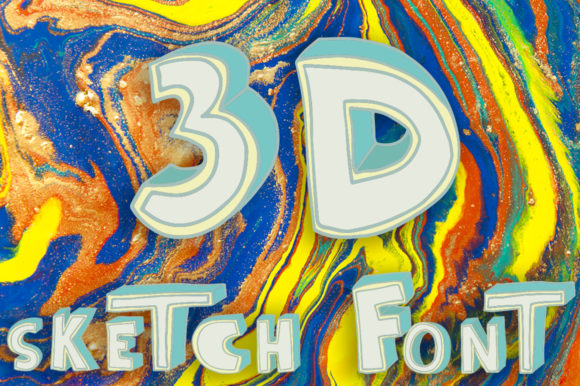
3D Sketch
Ulasan Mendalam: 3D Sketch – Font Display Urban yang Trendi
Jika Anda sedang mencari font display yang mampu menambah kesan modern dan urban pada desain grafis, 3D Sketch adalah pilihan yang tepat. Font ini memadukan gaya tiga dimensi dengan sentuhan street‑art, menjadikannya sangat versatile untuk berbagai proyek kreatif.
Keunggulan Utama 3D Sketch
- Desain 3D yang mencolok – Memberikan efek kedalaman yang membuat teks “melompat” dari latar belakang.
- Gaya urban & trendi – Cocok untuk branding streetwear, poster musik, event festival, dan kampanye media sosial.
- Kemudahan penyesuaian – Dapat di‑modifikasi warna, bayangan, dan ukuran tanpa kehilangan kualitas.
Penggunaan Ideal 3D Sketch
Berikut beberapa contoh di mana 3D Sketch dapat meningkatkan nilai visual proyek Anda:
- Logo merek streetwear atau sneaker brand.
- Header situs web musik, event live, atau festival.
- Cover album, single, atau mixtape dengan nuansa urban.
- Poster promosi film aksi atau video game.
- Grafik media sosial yang membutuhkan daya tarik visual cepat.
Mengapa Memilih 3D Sketch?
Dengan 3D Sketch, Anda tidak hanya mendapatkan sebuah font, melainkan sebuah alat kreatif yang memungkinkan eksplorasi tak terbatas. Kombinasi antara estetika tiga dimensi dan vibe kota membuatnya cocok untuk desain yang ingin menonjol di pasar yang kompetitif.
Jika Anda ingin menambahkan sentuhan futuristik dan urban pada karya visual, 3D Sketch adalah pilihan yang tidak boleh dilewatkan. Unduh sekarang, bereksperimen dengan warna serta efek, dan biarkan font ini menjadi pusat perhatian dalam setiap proyek desain Anda.